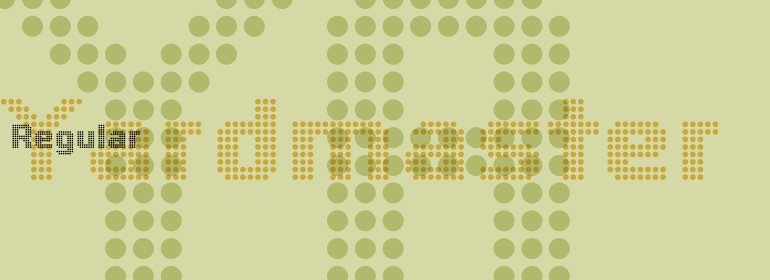
Yardmaster
Yardmaster,这款字体结构工整、笔画清晰,兼顾美观与易读性,适用于标题、正文、海报、包装、LOGO 等多种场景。字形优雅稳定,风格百搭耐看,适配日常排版与创意设计,让文字呈现更舒适、更具质感。Yardmaster一笔一画,皆是细节,以均衡的比例、流畅的线条打造舒适视觉体验,字形端正大气,风格简约现代。无论是商业设计、品牌宣传还是日常排版,都能轻松驾驭,让文字更有格调与力量。Yardmaster字体下载。
字体品牌: Linotype(Monotype) 设计师:Napp,Karl 字体分类:衬线体 字体属性:外文 字符集:Unicode 发布时间: 2018